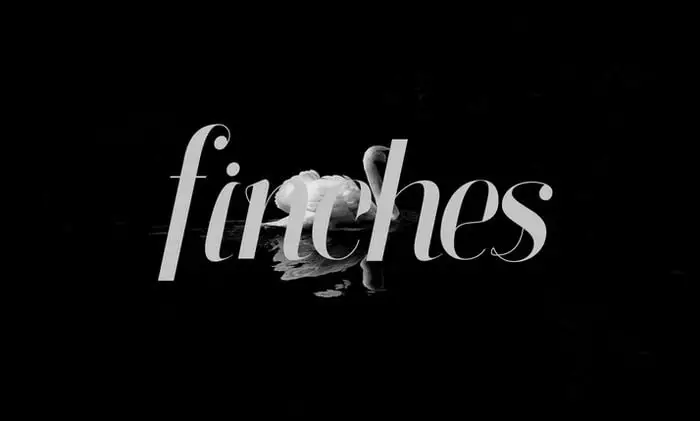
Introduzimos a Finches Typeface! Esta família de letras sólidas apresenta um ar semi-cleaneiro com uma boa precisão. Afinhas foram criadas e compartilhadas pela Graphic Pear, e combinam perfeitamente para qualquer design que você possa fazer. A combinação da Finches é perfeita para uso em logos de roupas, como a sua marca ou o seu estilo vintage. Ela se destaca especialmente quando aplicada ao logo do produto ou no card de casamento, tornando-se um elemento distintivo e impecável para branding fashion. A Finches também será uma excelente escolha para qualquer projeto vintage que você está planejando. Essas fontes são perfeitas para personalizar logotipos, desde os mais modernos até aqueles com toques vintage, garantindo sempre uma apresentação de alto padrão e profissionalismo. Escolha a Finches para sua próxima criação gráfica – seu design vai ficar ainda melhor!